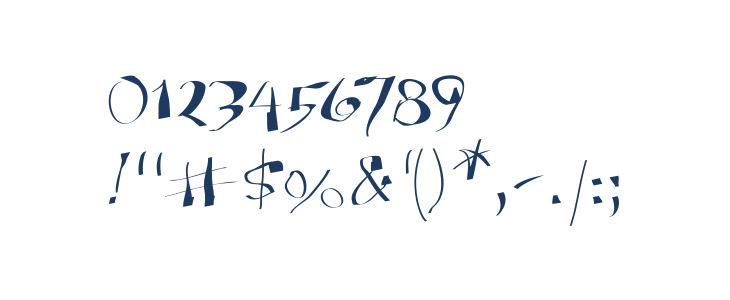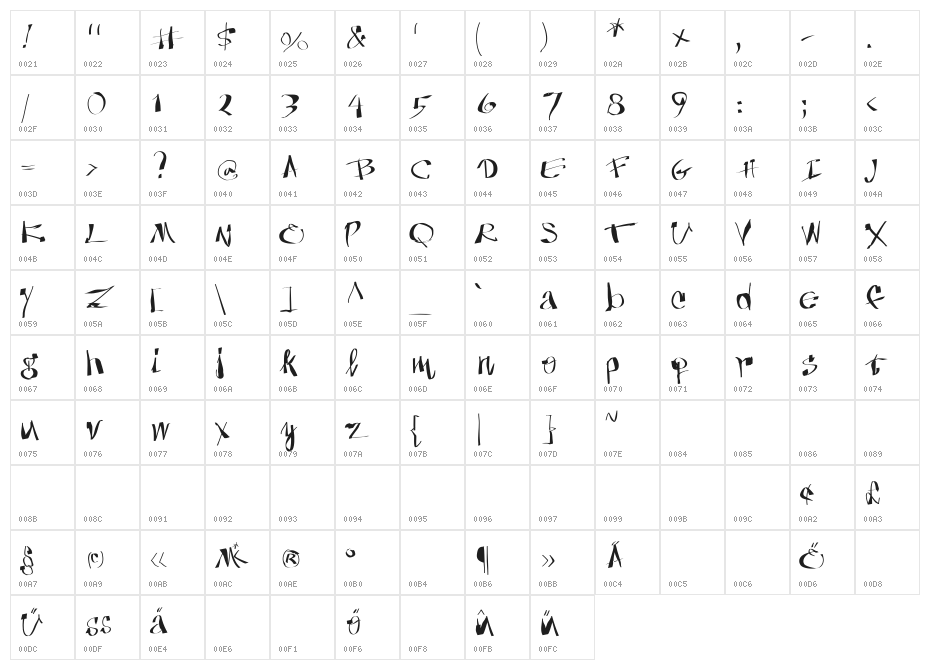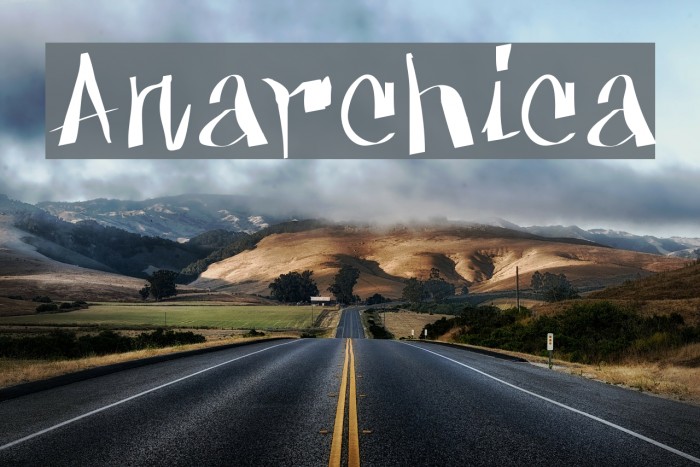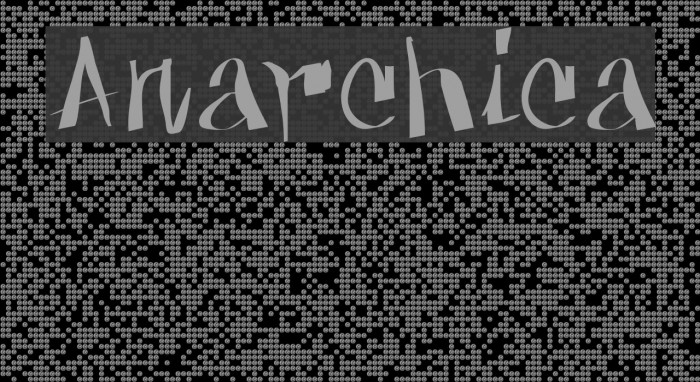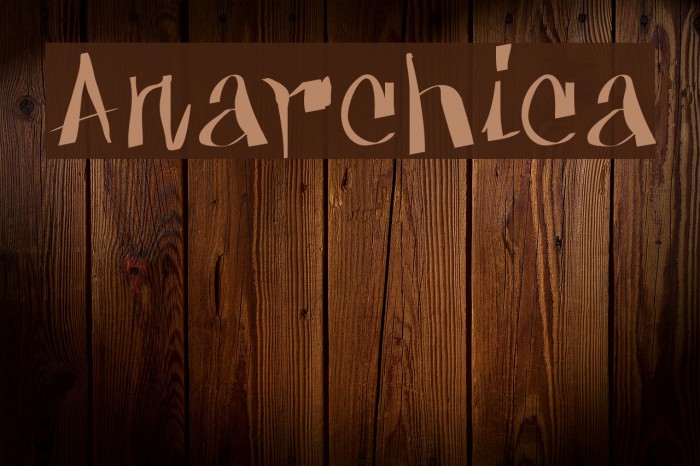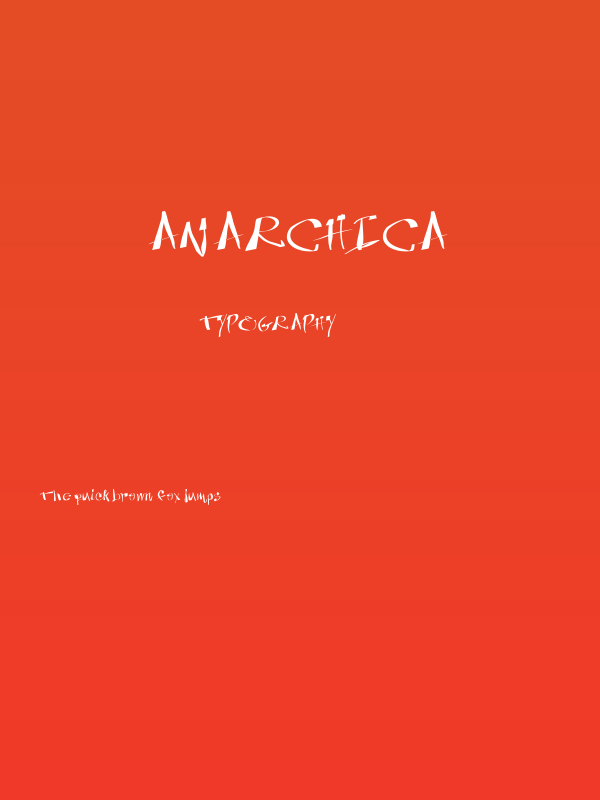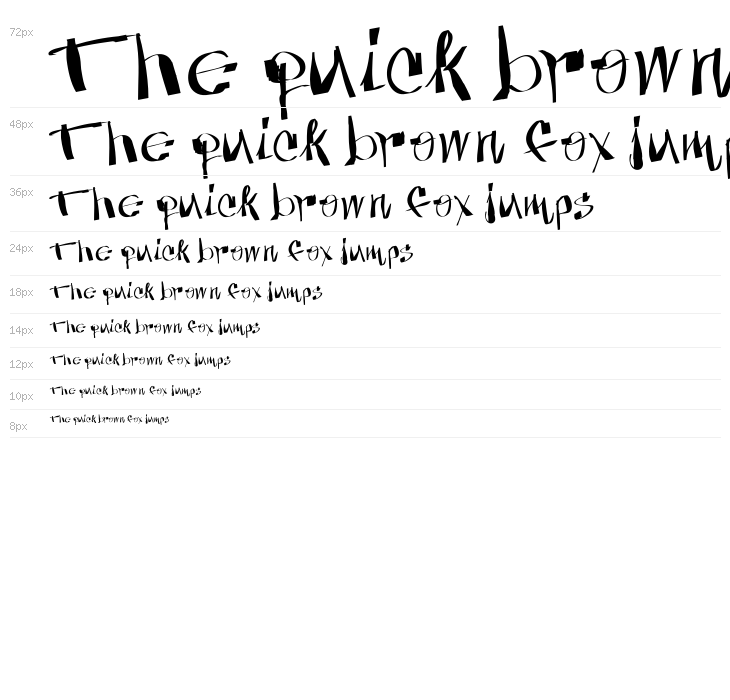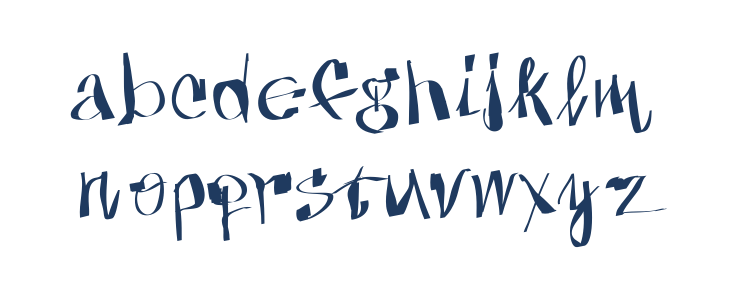
Anarchica Font
| Stile generale | Modern, Edgy |
| Progetti proposti | Ideal for street art designs, music album covers, edgy branding, and posters that require a bold statement. |